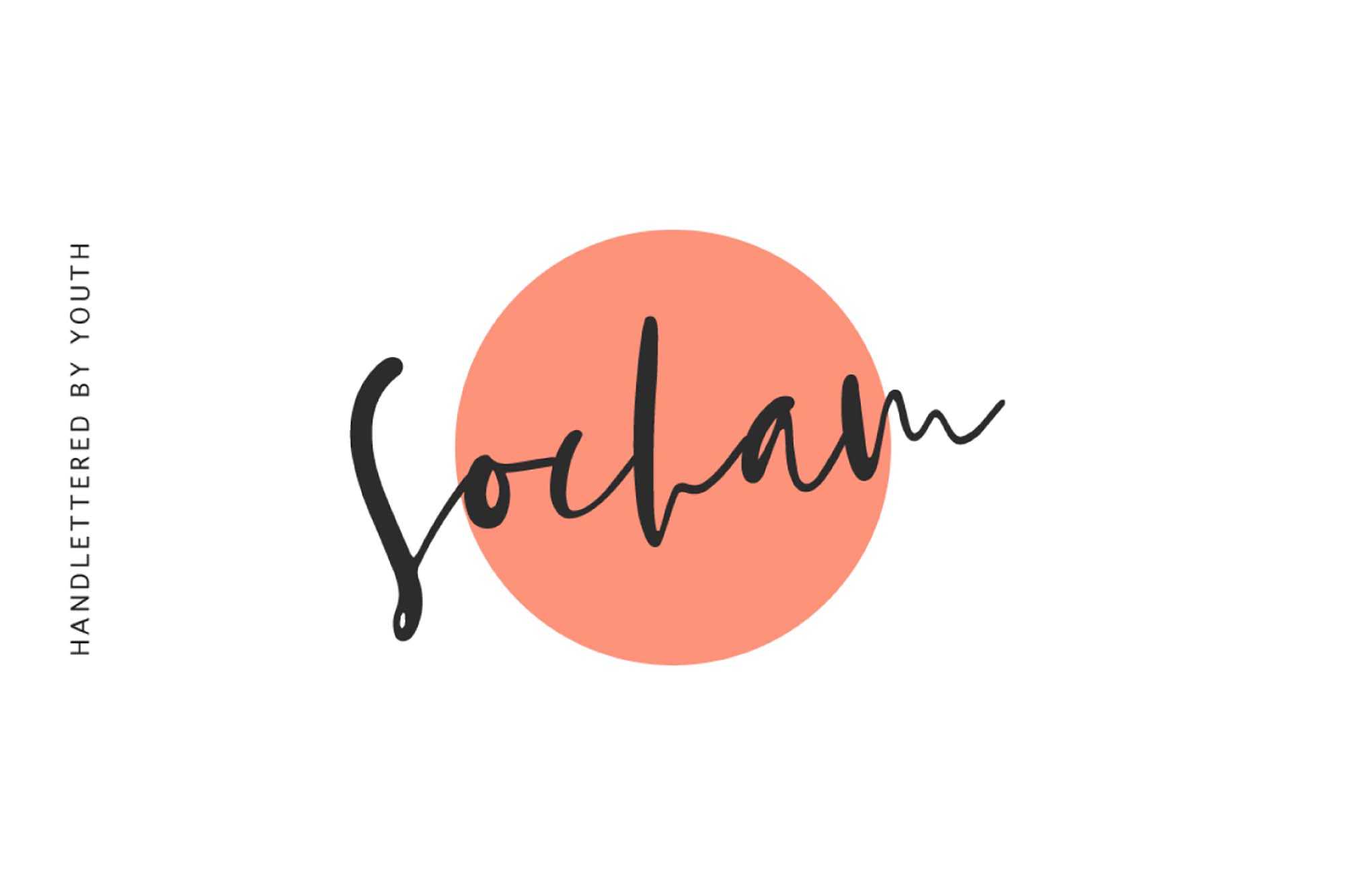
Socham Calligraphy Script Font – Download Grátis
A fonte de script “Socham” é perfeita para aqueles que buscam um equilíbrio sutil entre elegância e estilo, sem comprometer a personalidade. Este tipo de fonte é ideal para designers que buscam dar um toque distintivo e sofisticado a seus projetos. Seja para um layout com uma linha de base leve e caracteres sedutoramente femininos, ou para experimentar grunge e letras texturizadas, a fonte de script “Socham” tem você coberto. Seja qual seja o seu estilo, a “Socham” certamente irá tornar seu trabalho ainda mais interessante e único. Essa fonte de script moderna e sofisticada é a escolha perfeita para quem busca um ar descontraído, mas mantém a elegância no design.